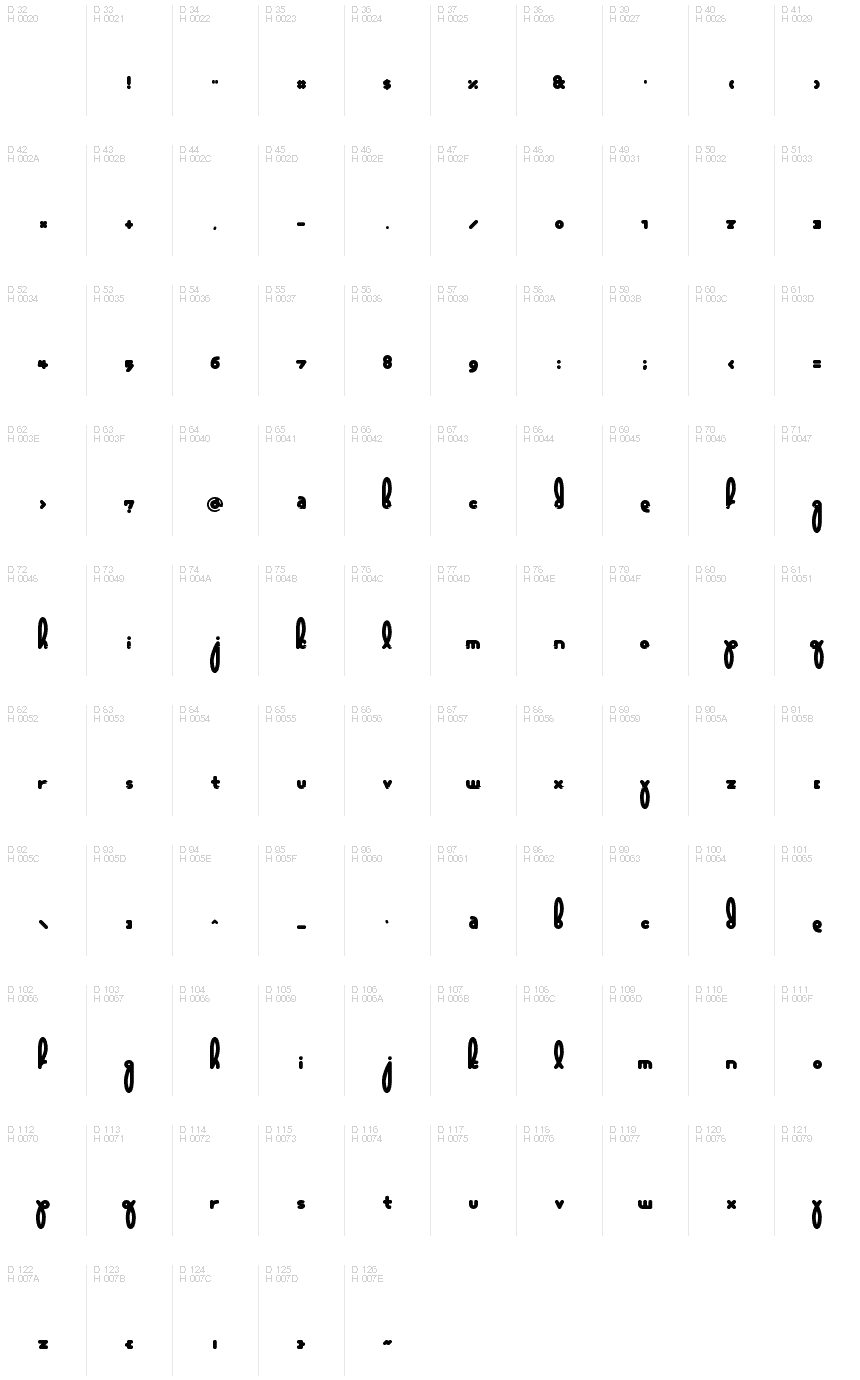
Bunny Alphabet 字体
Bunny Alphabet
Bunny Alphabet 由 Flop Design 设计,是一款免费的漫画风显示字体,将可爱的兔子主题直接融入到了字母设计中。圆润的字形柔软且充满童趣,而长长的兔耳状圆圈和垂坠的曲线赋予了这款字体生动的跳跃感,使其摆脱了普通气泡字体的平庸。
它非常适合儿童绘本封面、复活节传单、派对邀请函、商店招牌以及短小精悍的 Logo 设计,这款带有明确吉祥物元素的免费字体能帮助您快速传达信息。请在标题、名牌或简短的文字中使用它,因为这些兔耳朵造型的细节本身就极具表现力。